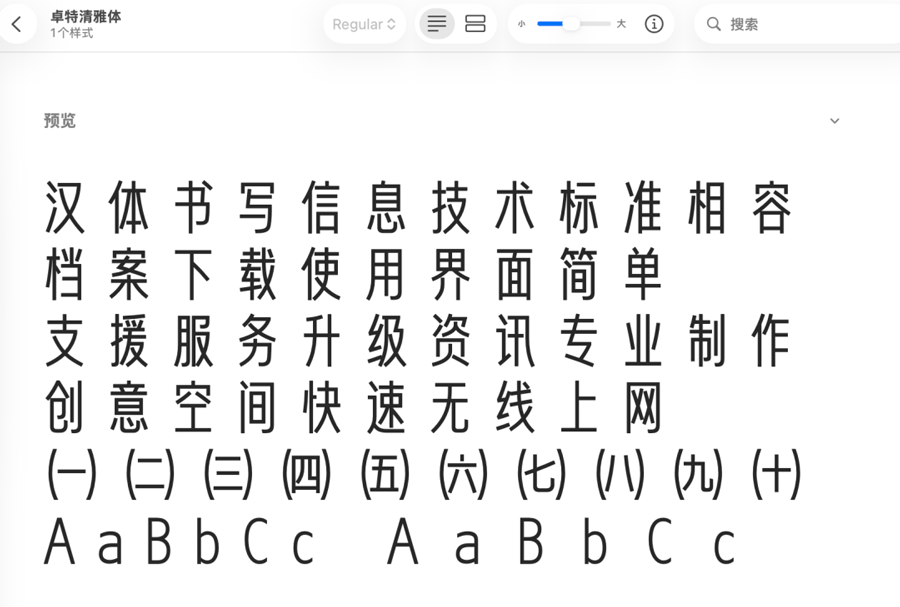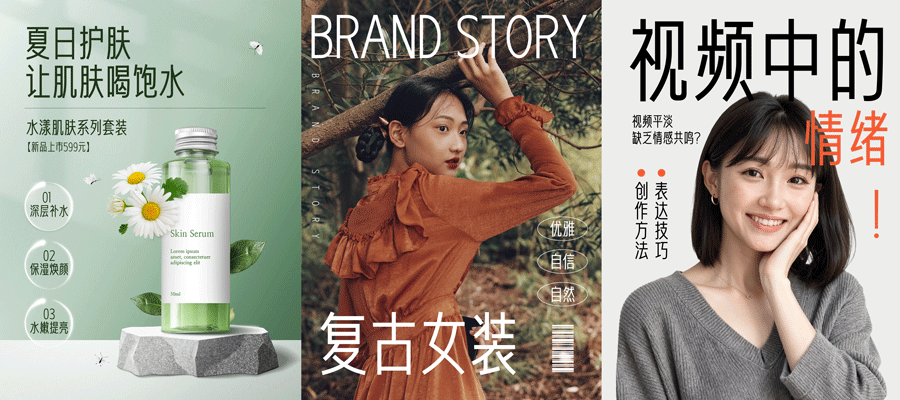
卓特清雅体
卓特清雅体是创意素材库卓特视觉携手国内知名字体设计师刘兵克推出的三款免费开源字体(卓特清雅体、卓特悦动黑卓特自由体)中的一种。
卓特清雅体的字形设计瘦长,整体呈现出挺拔的姿态,笔画线条简洁明了,没有多余的装饰,而且重心稳定,中宫收紧,不管是大字号需要的视觉效果,还是小字号需要的排版清晰,卓特清雅体都能适用。